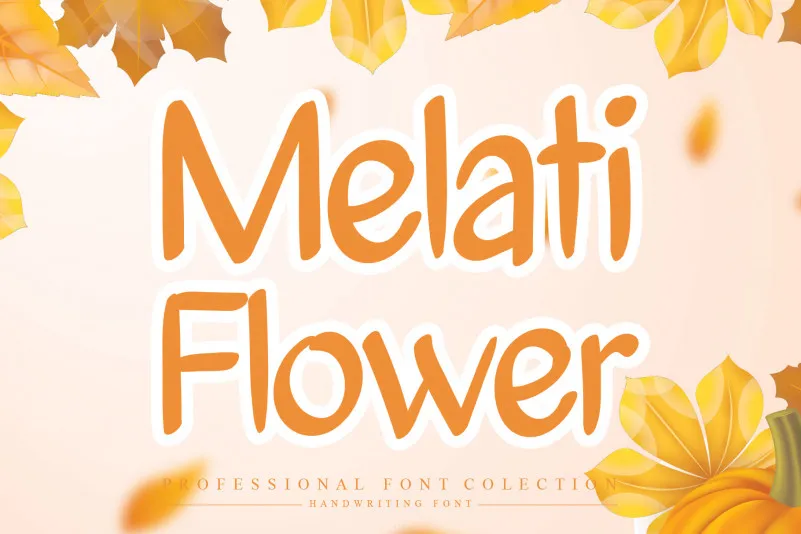
Melati Flower Brush Font – Download Grátis
A fonte ‘Melati Flower Brush’ é uma escolha perfeita para aqueles que buscam um toque delicado e único no design. Ela vem em forma de traços delicadamente escritos, simples e agradavelmente neat. Ideal tanto para uso pessoal quanto profissional, essa fonte oferece um estilo casual mas altamente atraente, capaz de dar vida aos mais variados projetos gráficos. A sua categoria como uma fonte ‘script’ a torna perfeitamente adaptável a criações que exijam uma mão real escrita, seja em logotipos, selos ou até mesmo letras de música. Seja qual for o seu projeto, é impossível não notar o toque especial que esta fonte traz à sua obra. Para designer e não só, ‘Melati Flower Brush’ oferece a oportunidade de criar um design que impressionará seus espectadores, elevando-o a níveis inimagináveis. Seja você um artista digital ou alguém que trabalha em uma área de arte gráfica, ‘Melati Flower Brush’ é uma fonte que merece ser explorada e adotada no seu portfólio.